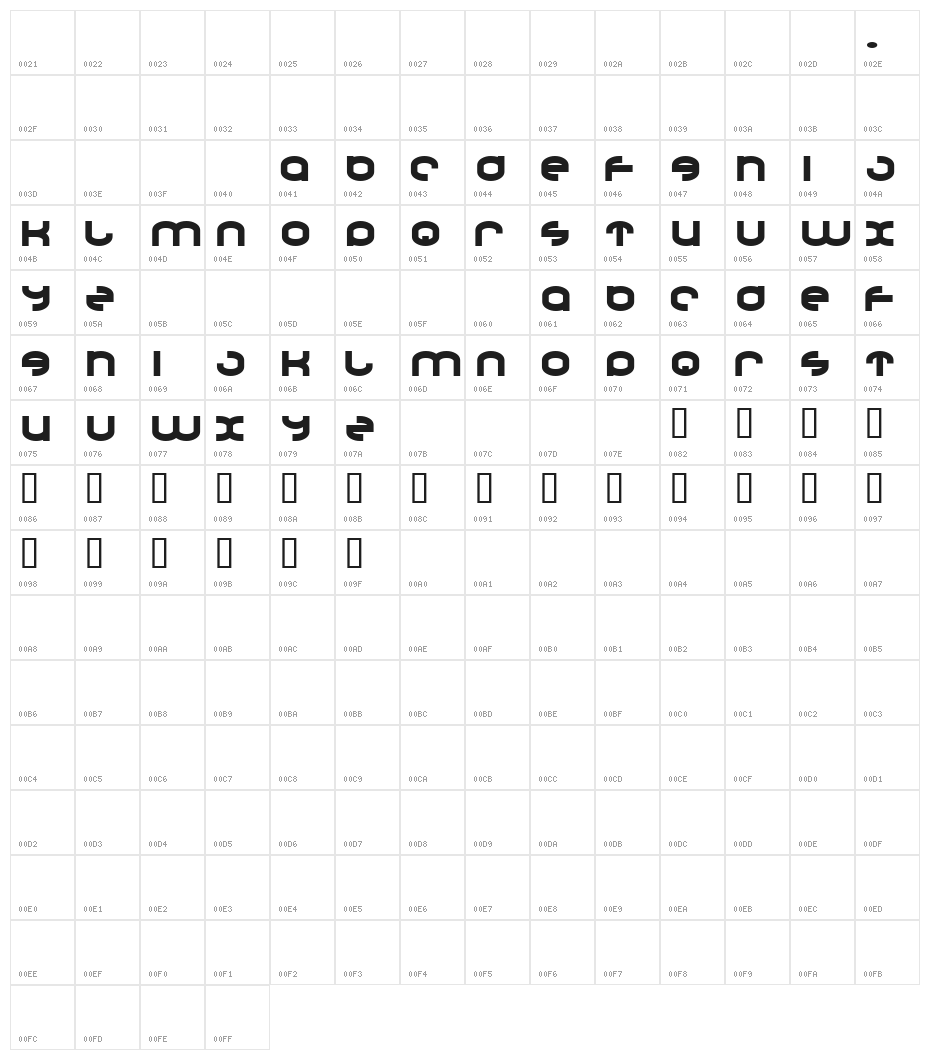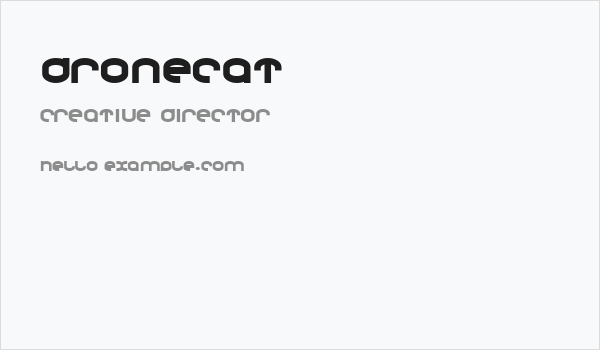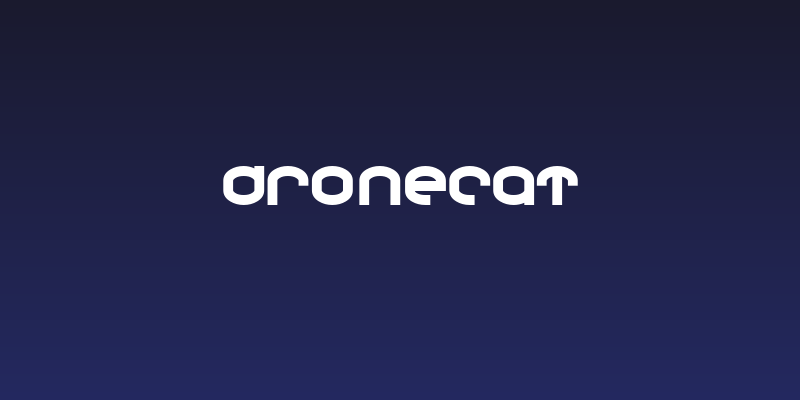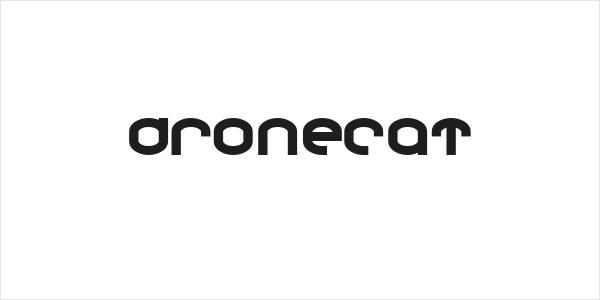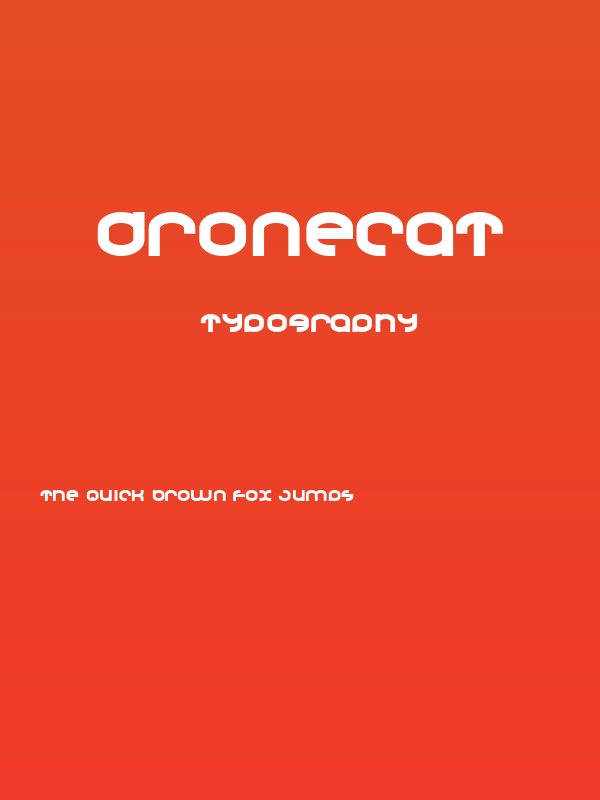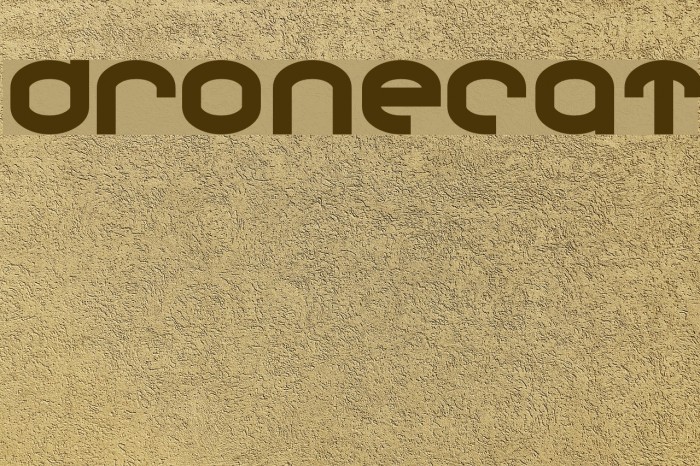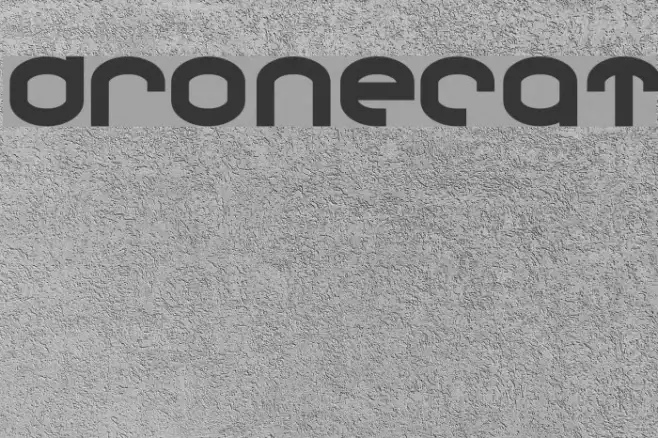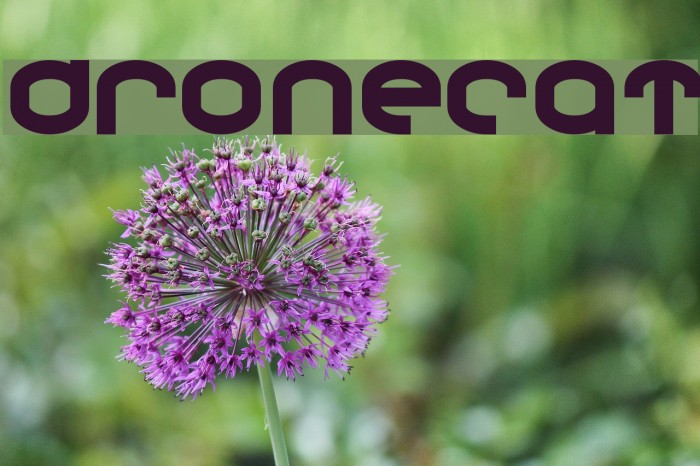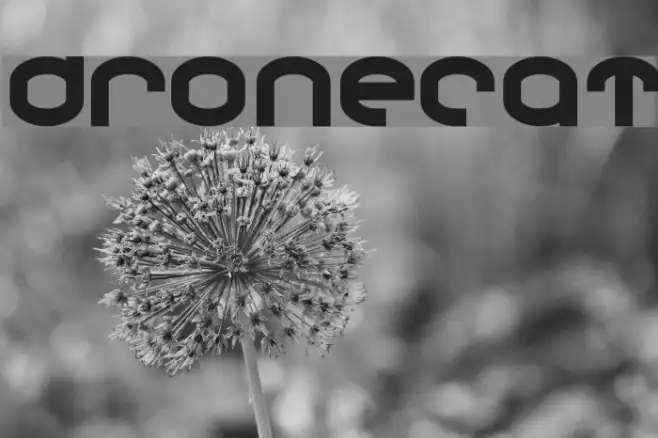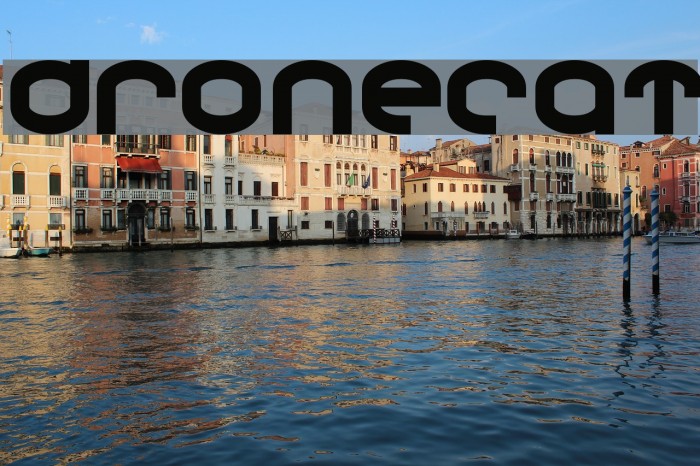
Dronecat Font
| Anwendungsfall | Logos, Headlines, Posters |
| Vorgeschlagene Projekte | Ideal for technology branding, sci-fi themed designs, modern advertising, and innovative product packaging. |